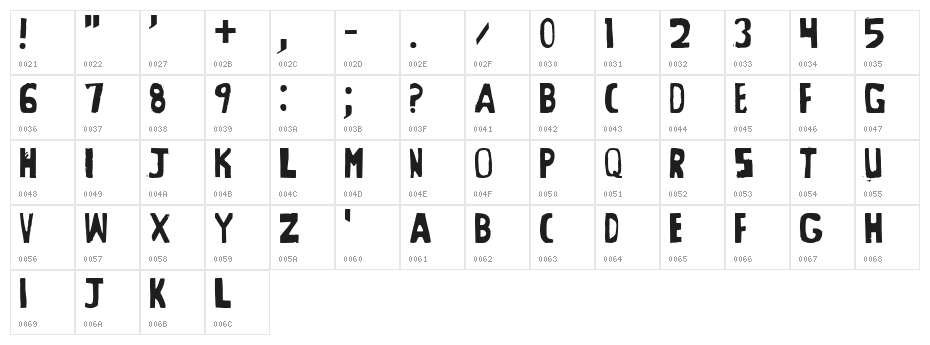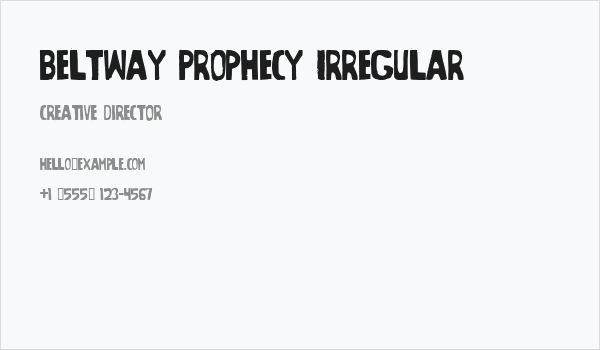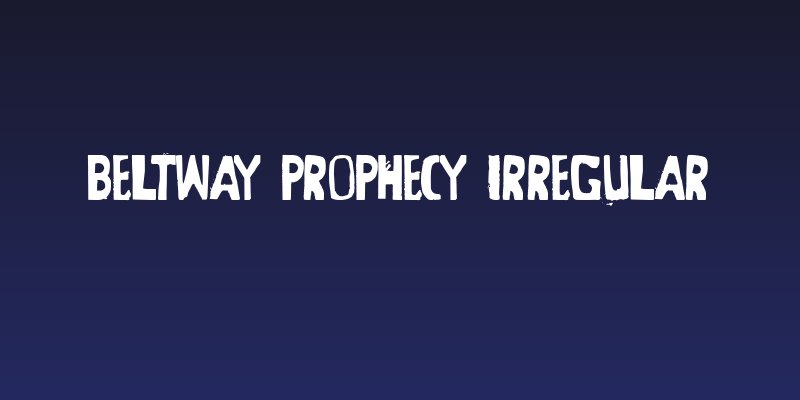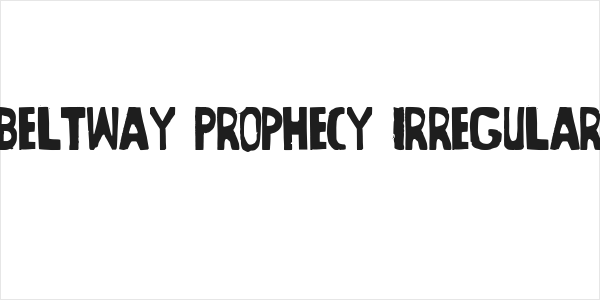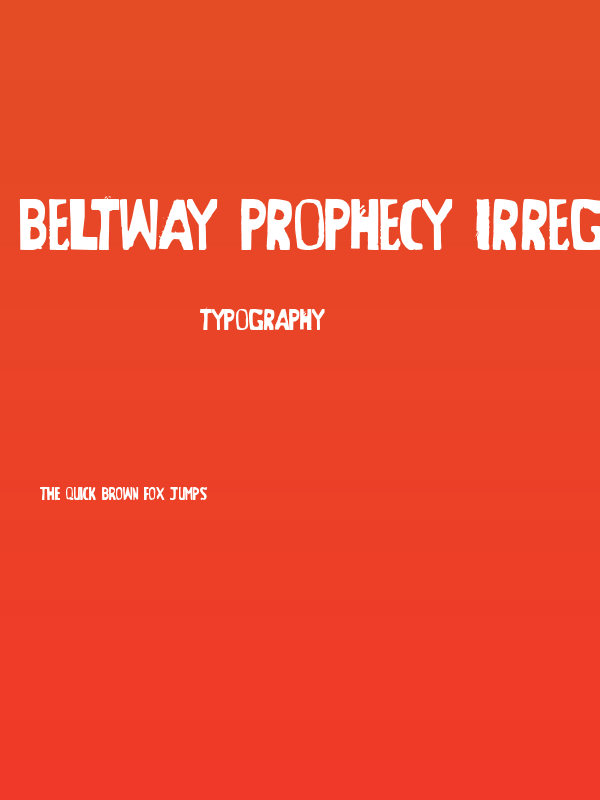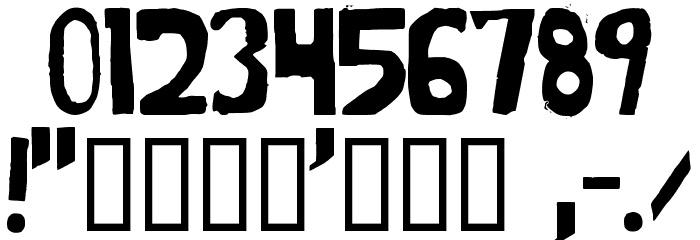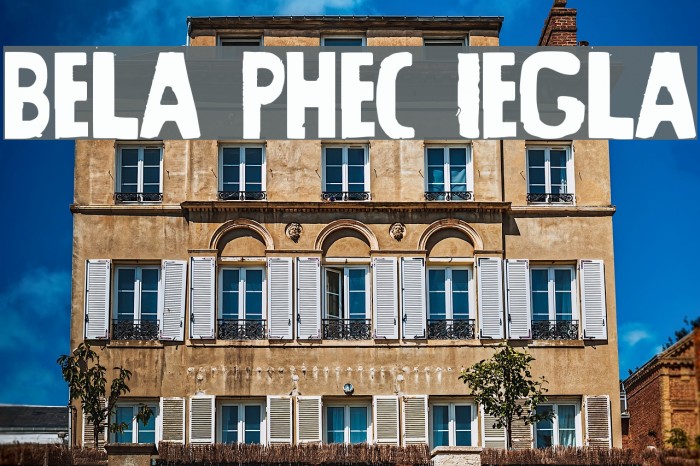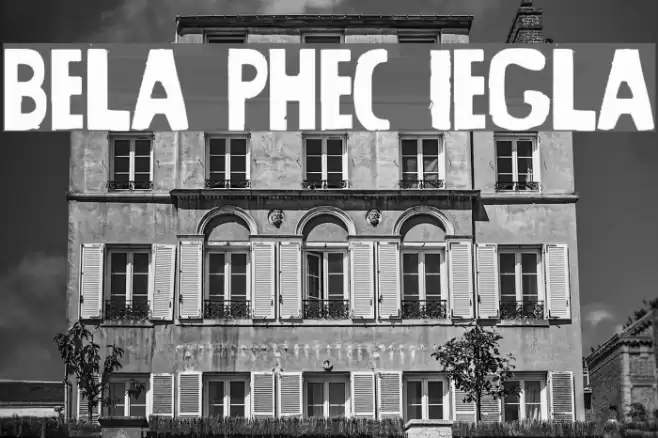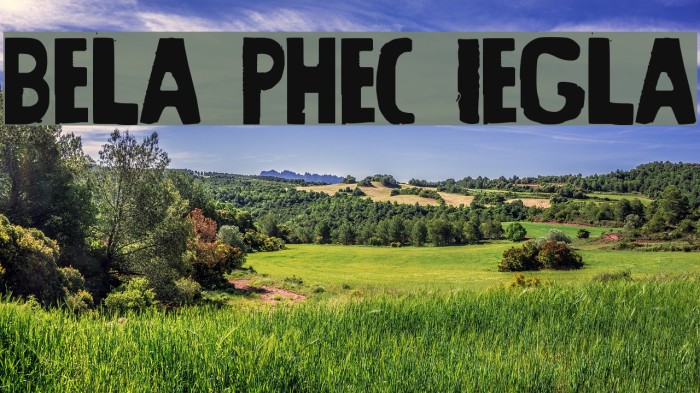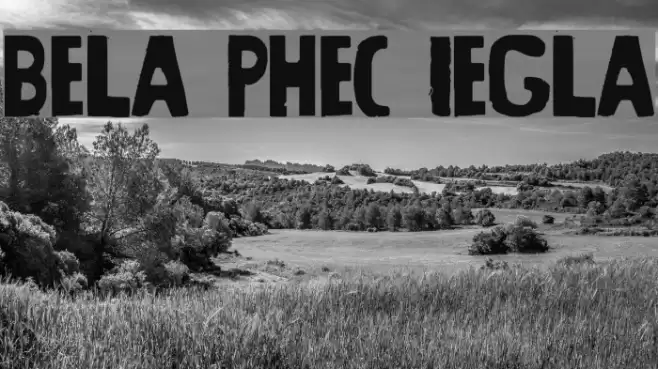
Beltway Prophecy Irregular Font
BELTWAY-PROPHECY-IRREGULAR Groß
BELTWAY-PROPHECY-IRREGULAR Kleinbuchstaben
BELTWAY-PROPHECY-IRREGULAR Anderer Schreiben
| Name | Beltway Prophecy Irregular |
| Gewicht | Irregular |
| Kategorien | Capitals |
| Vorgeschlagene Projekte | Ideal for posters, album covers, branding for artisanal products, or any project needing a bold, rustic aesthetic. |